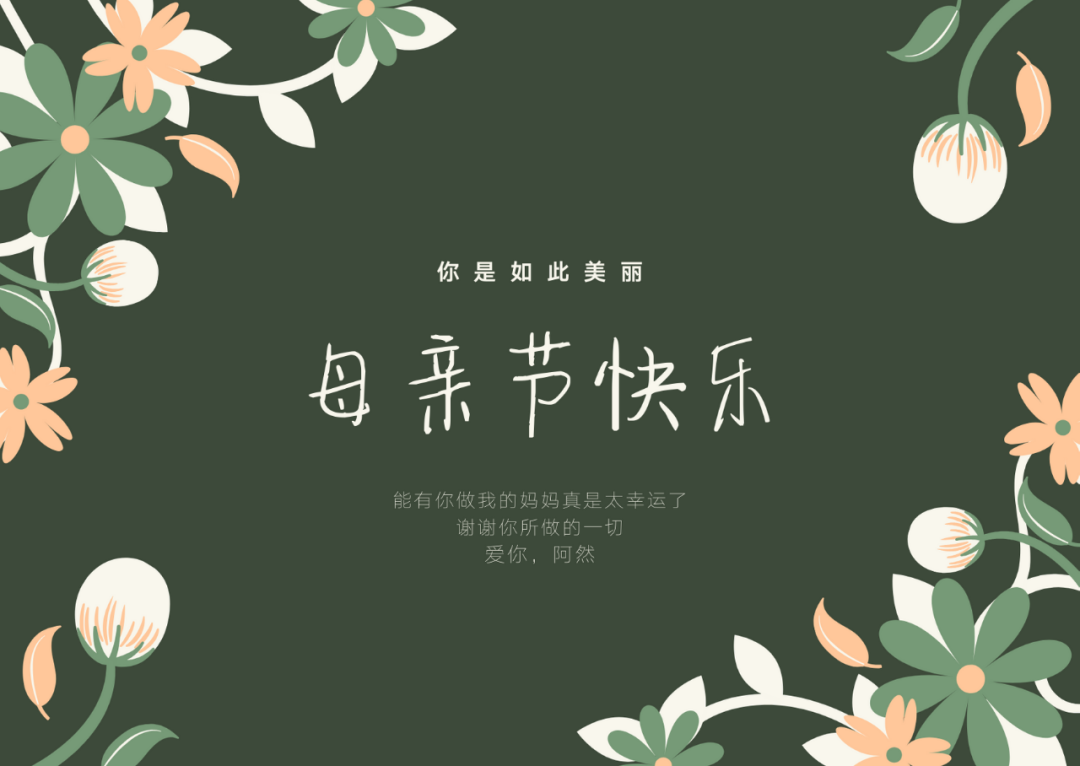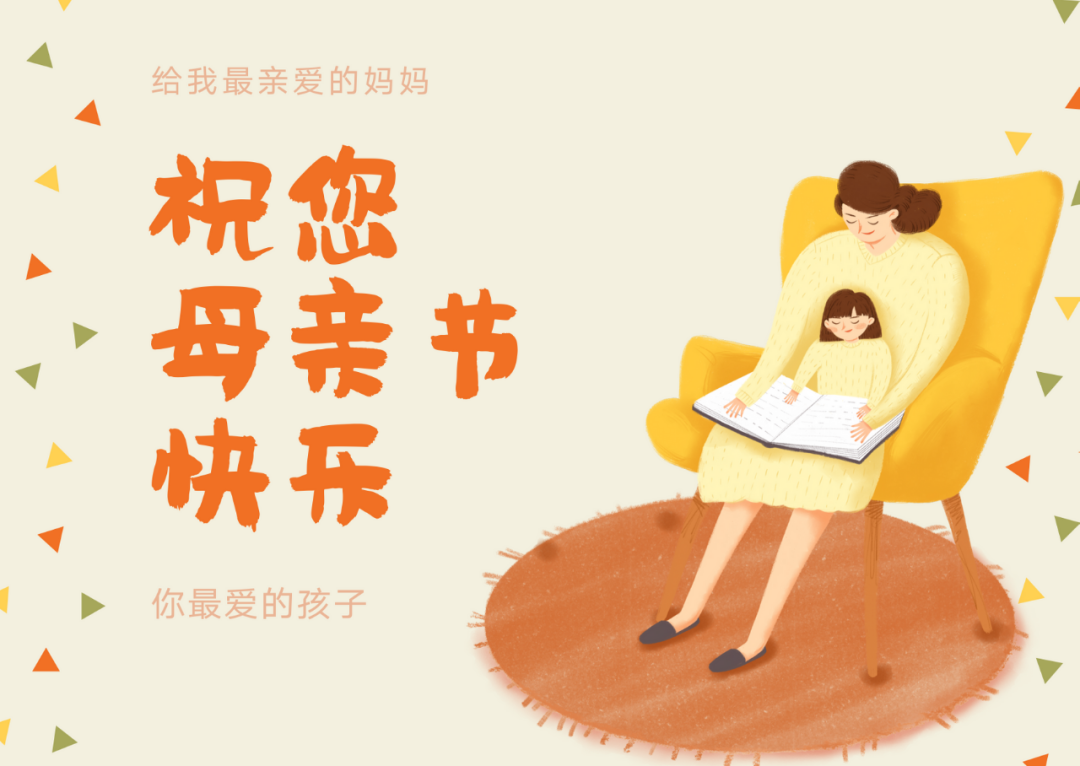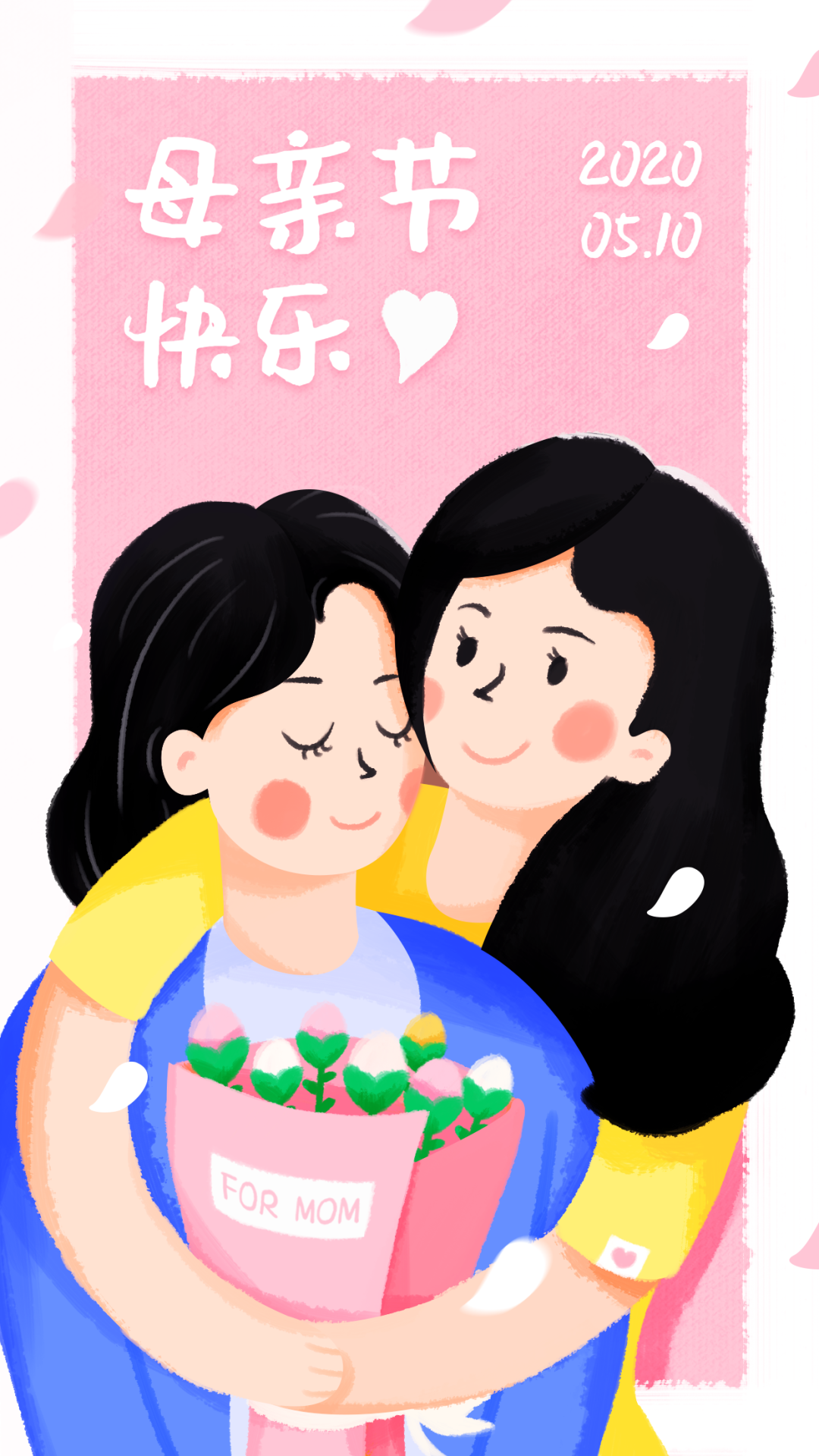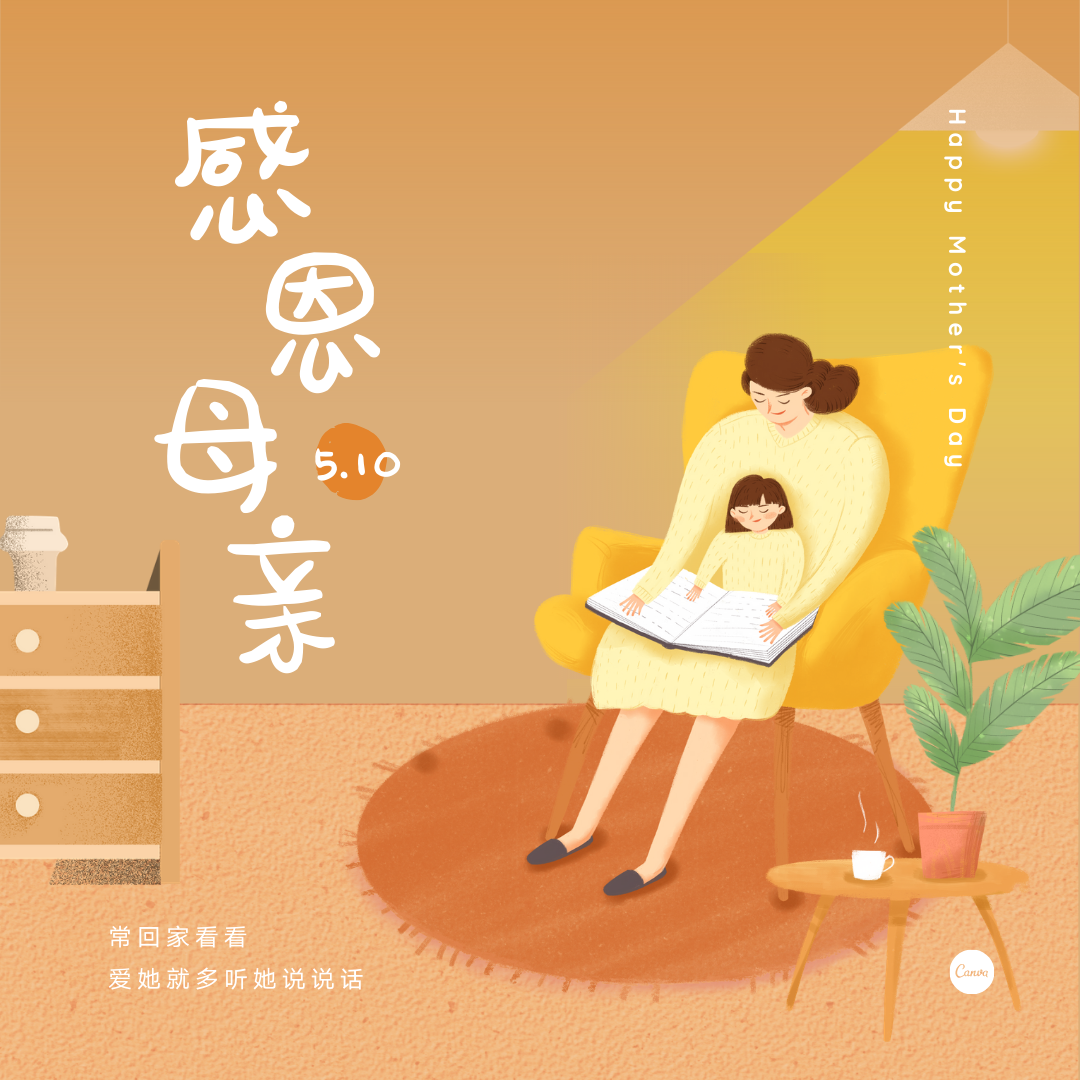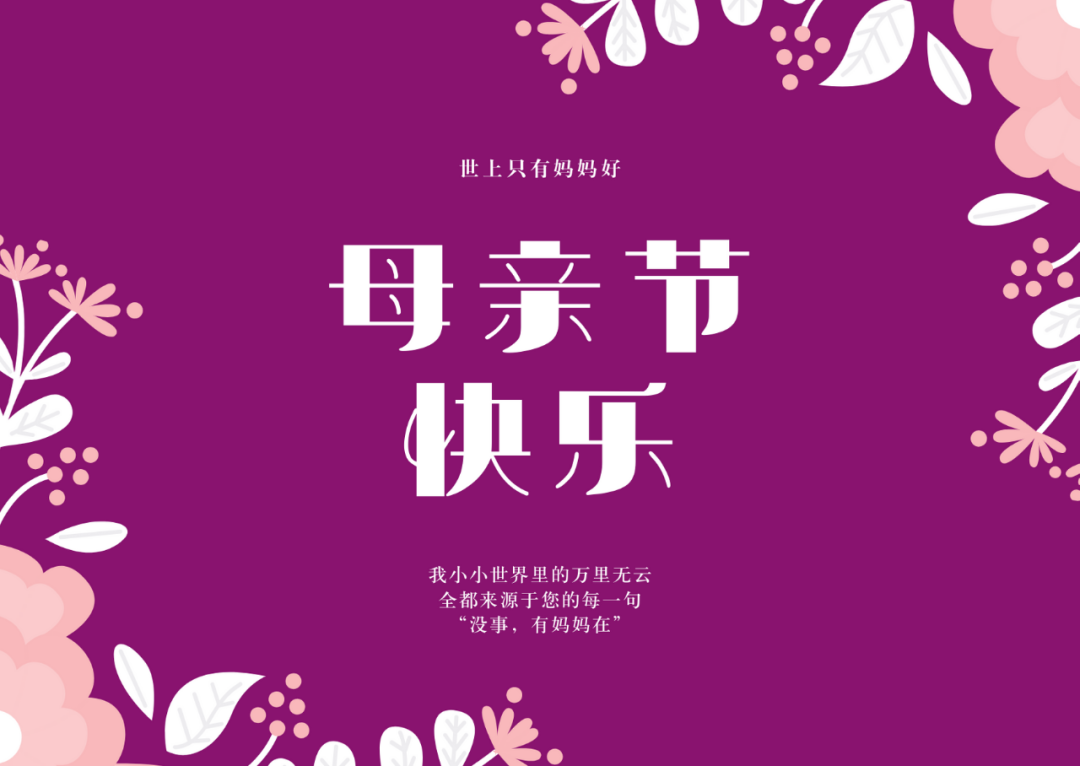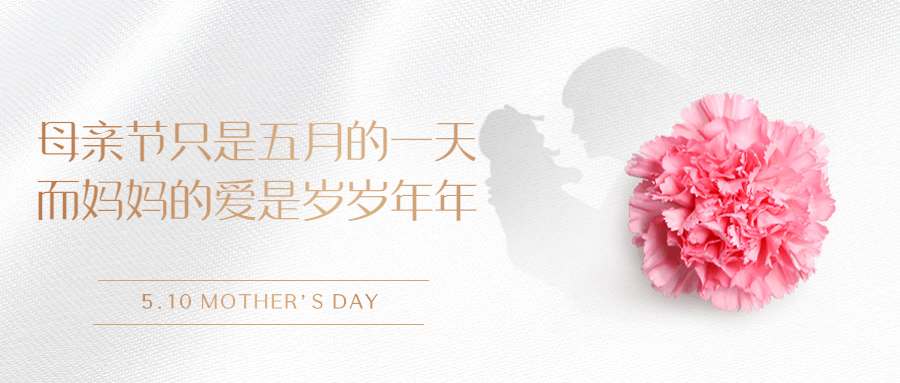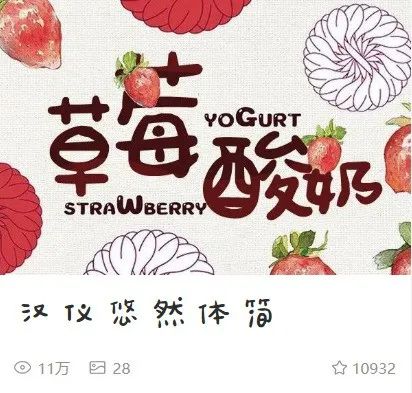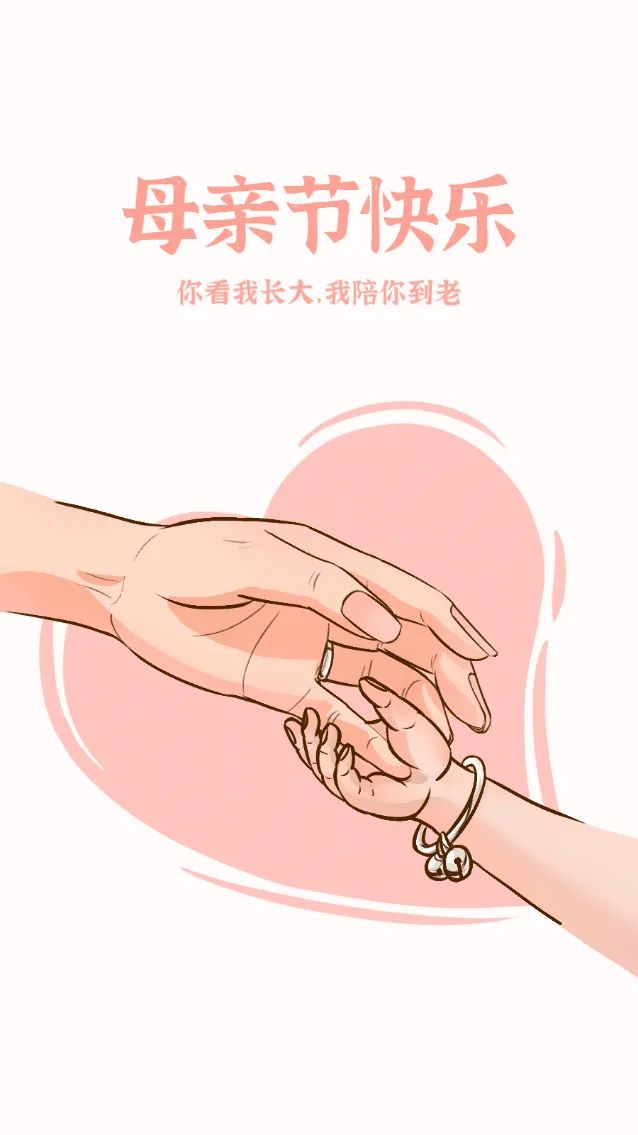
母亲节的图做完了吗?赶紧用这些字体救救急
后天就是母亲节了,你的图做完了吗?趁还有一天,赶紧临时抱个佛脚,字体柚子都给你选好了~
温暖的手写体
手写体最有温度,所以很适合510这种温情满满的节日~
充满爱意的字体
除了手写体,看起来圆润有趣的字体,也很适合母亲节,像极了孩子跟麻麻撒娇的感觉。
怀念时光的字体
最后是有一定年代感的字体,能让人追忆似水年华。